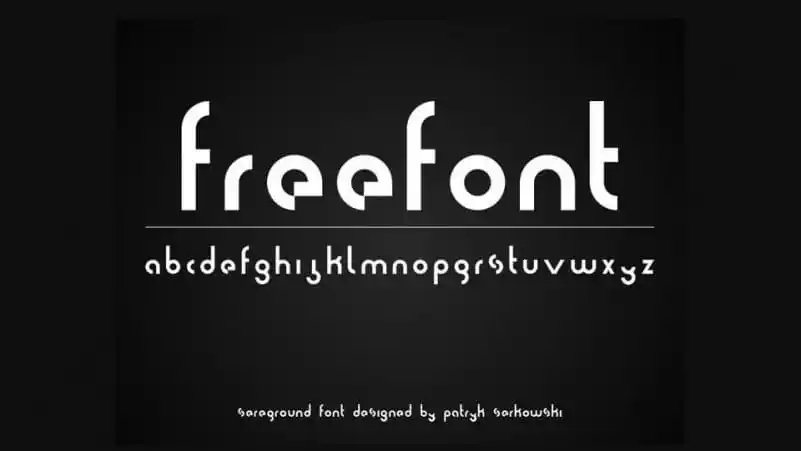
Sereq Display Font – Download Grátis
A Sereq Display Font é inspirada no tema de aeronaves espaciais, criada com formas geométricas simples. Patryk Serkowski, o designer do tipo de texto, abraçou essa ideia única para criar uma fonte que traz um toque moderno e desafiador. Sereq oferece uma experiência visual interessante graças aos seus formados irregulares, tornando-se perfeita para aplicar em campanhas visuais criativas. Esta fonte é especialmente adequada para aplicações gráficas como posteres, headlines e logotipos, onde sua geometria simples e seu formato redondo contrastam de maneira impactante. Com duas opções de estilo – Regular e Outline – e suporte ao português, a Sereq Display Font é um recurso gráfico indispensável que adicionará uma dose de originalidade à qualquer projeto visual.